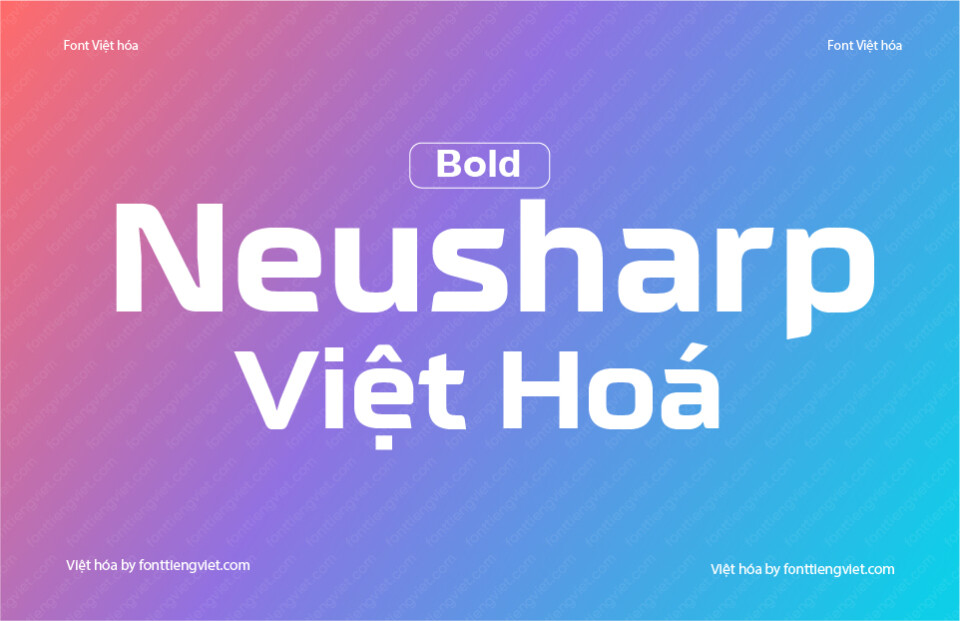
Font Việt hóa 1FTV VIP Neusharp Bold
Trong thế giới thiết kế đồ họa hiện đại, việc lựa chọn một bộ font chữ phù hợp đóng vai trò then chốt trong việc truyền tải thông điệp và tạo dấu ấn thị giác. Đặc biệt đối với các nhà sáng tạo nội dung tại Việt Nam, nhu cầu tìm kiếm các bộ phông chữ đã được tinh chỉnh dấu tiếng Việt là rất lớn. Font Việt hóa 1FTV VIP Neusharp Bold nổi lên như một lựa chọn hàng đầu nhờ sự kết hợp hoàn hảo giữa phong cách hiện đại, mạnh mẽ và tính ứng dụng cao. Khi nhắc đến khái niệm Font Miễn Phí, người dùng thường mong đợi một sản phẩm không chỉ đẹp mà còn phải hiển thị mượt mà trên mọi thiết bị. Bộ Font Việt hóa 1FTV VIP Neusharp Bold chính là câu trả lời lý tưởng cho những ai đang tìm kiếm sự đột phá trong các dự án từ thiết kế UI/UX đến in ấn quảng cáo.
Đặc điểm nổi bật của Font Việt hóa 1FTV VIP Neusharp Bold
Font Việt hóa 1FTV VIP Neusharp Bold thuộc họ font Sans-serif với các đường nét được cắt gọt dứt khoát, mang lại cảm giác công nghiệp và công nghệ. Điểm mạnh lớn nhất của bộ font này là độ dày (bold) lý tưởng, giúp các tiêu đề trở nên nổi bật và thu hút sự chú ý ngay lập tức. Các ký tự tiếng Việt như á, ớ, hay đ được đội ngũ 1FTV chăm chút tỉ mỉ, đảm bảo không có hiện tượng lỗi dấu hay lệch khoảng cách giữa các chữ cái, một vấn đề thường gặp ở các bản font nguyên gốc chưa được tối ưu hóa.
Tính ứng dụng linh hoạt trong giáo dục và thiết kế
Đối với các bạn học sinh và sinh viên, Font Việt hóa 1FTV VIP Neusharp Bold là công cụ đắc lực để thiết kế các bài thuyết trình, poster câu lạc bộ hay làm bìa báo cáo học tập. Sự rõ ràng của font giúp người xem dễ dàng tiếp nhận thông tin dù ở khoảng cách xa. Trong môi trường sư phạm, giáo viên cũng có thể sử dụng bộ font này để làm mới giáo án điện tử, giúp bài giảng trở nên sinh động và hiện đại hơn. Sự kết hợp giữa nét thẳng và các góc bo nhẹ mang lại cảm giác thân thiện nhưng vẫn giữ được sự chuyên nghiệp cần thiết cho mọi sản phẩm giáo dục.
Sử dụng Font Việt hóa 1FTV VIP Neusharp Bold giúp bạn tiết kiệm đáng kể thời gian trong việc căn chỉnh thủ công các ký tự tiếng Việt phức tạp. Thay vì phải vật lộn với những font chữ nước ngoài bị lỗi hiển thị, bản Việt hóa này cho phép bạn tập trung hoàn toàn vào tư duy sáng tạo. Hơn nữa, phong cách Neusharp Bold rất dễ phối hợp với các bộ font mảnh hơn (Thin hoặc Light) để tạo ra sự tương phản thị giác thú vị, giúp bố cục thiết kế của bạn có chiều sâu và chuyên nghiệp hơn hẳn so với việc chỉ sử dụng các phông chữ hệ thống đơn điệu.
Lưu ý khi sử dụng bộ font trong các dự án thực tế
Dù là một bộ font mạnh mẽ, người dùng nên cân nhắc sử dụng Font Việt hóa 1FTV VIP Neusharp Bold chủ yếu cho các phần tiêu đề (Heading) hoặc các đoạn văn ngắn cần nhấn mạnh. Việc sử dụng quá nhiều font chữ đậm cho các đoạn văn dài có thể gây mỏi mắt cho người đọc. Hãy kết hợp khéo léo với không gian trắng (white space) để font chữ có “khoảng thở”, giúp tôn vinh được vẻ đẹp của từng đường nét hình học mà bộ font này mang lại. Đây thực sự là một mảnh ghép hoàn hảo cho bộ sưu tập tài nguyên của bất kỳ designer nào.
Kết luận về bộ Font Việt hóa 1FTV VIP Neusharp Bold